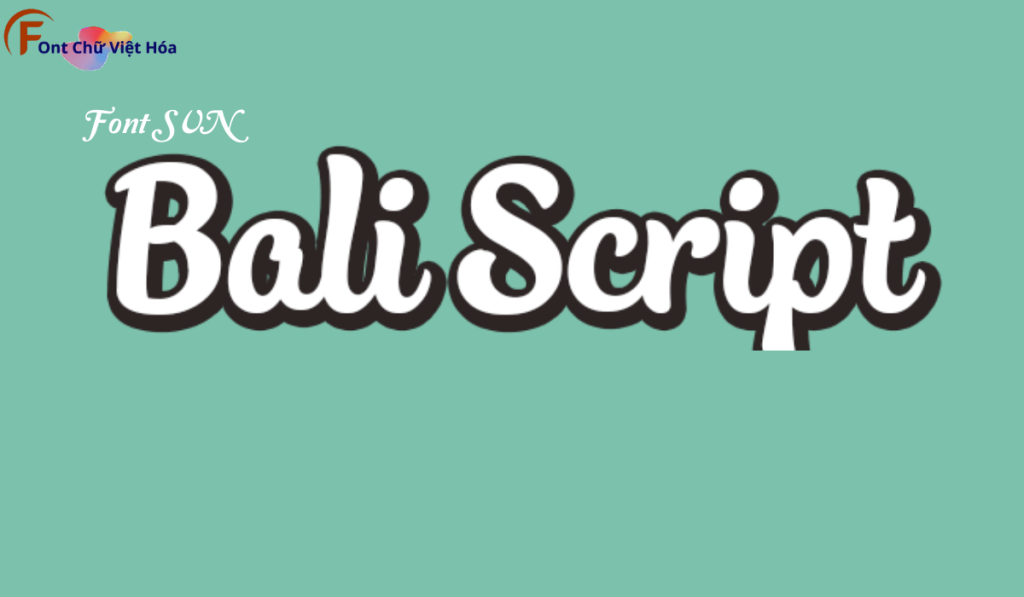
Bali SVN Font Việt Hóa
Tác giả: Bali SVN
Bộ Font: SVN
Kiểu chữ: Có chân
Độ dày: Loại thường
Bali SVN Font Việt Hóa là một font chữ không chân hiện đại, thuộc bộ font SVN. Được thiết kế với mục tiêu mang lại sự tinh tế và thanh lịch, font này phù hợp cho các dự án thiết kế như website, tài liệu, và bao bì sản phẩm. Với các nét chữ rõ ràng và độ dày đều đặn, Bali SVN Font Việt Hóa không chỉ dễ đọc mà còn tạo cảm giác chuyên nghiệp. Việc Việt hóa font giúp người dùng dễ dàng sử dụng trong các thiết kế tiếng Việt, mang lại sự tiện lợi và thẩm mỹ cao.